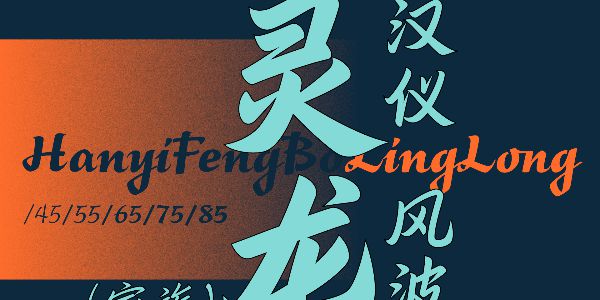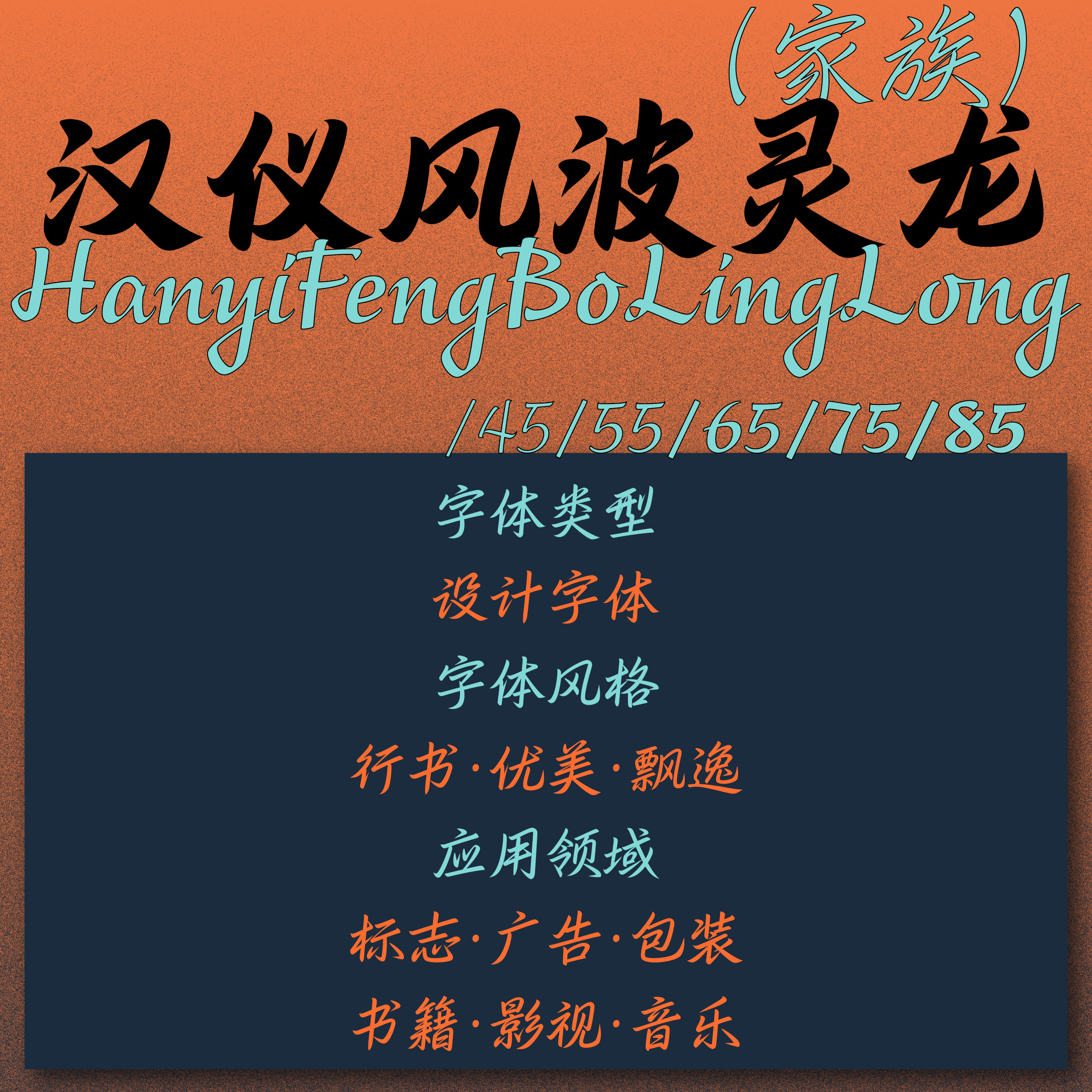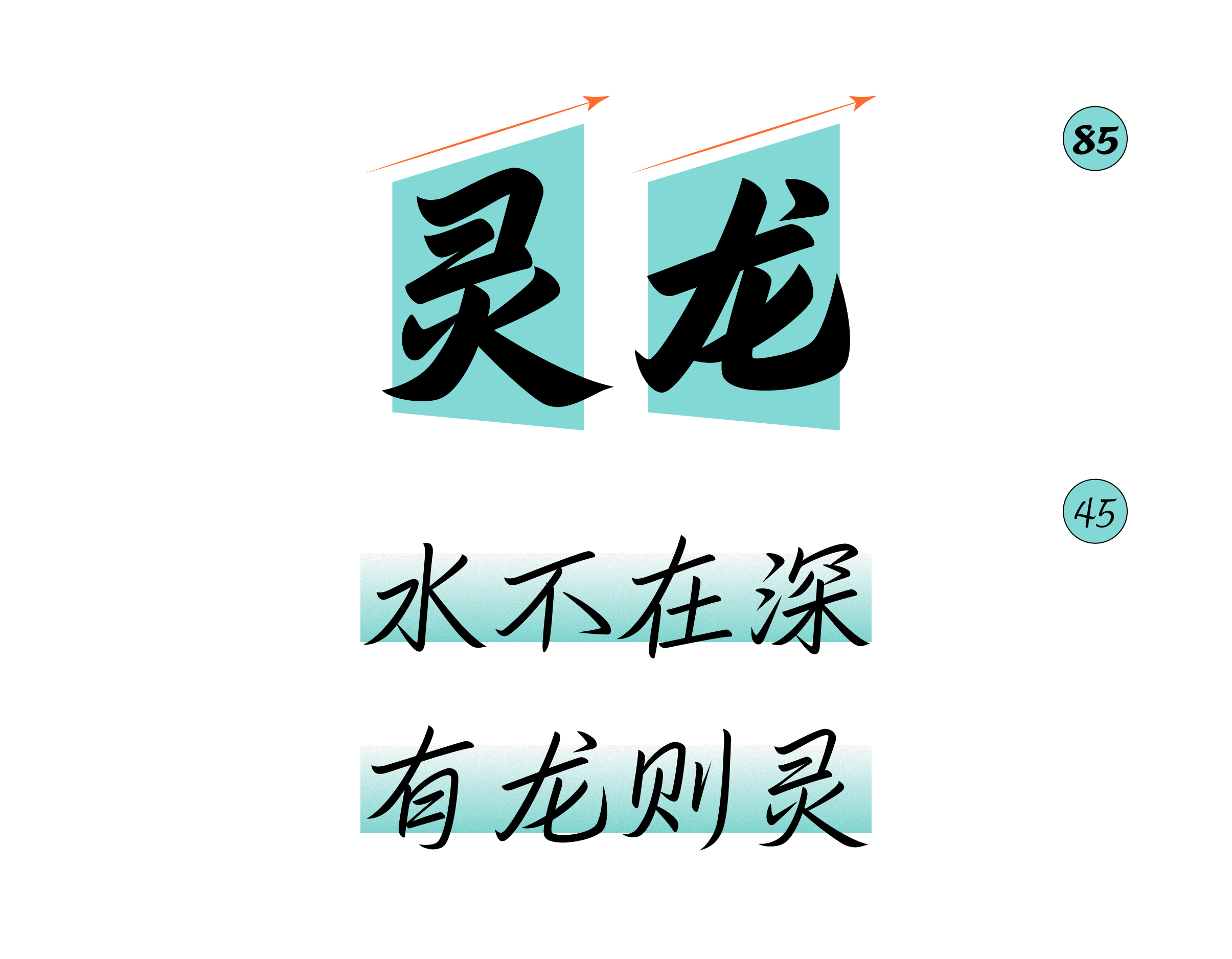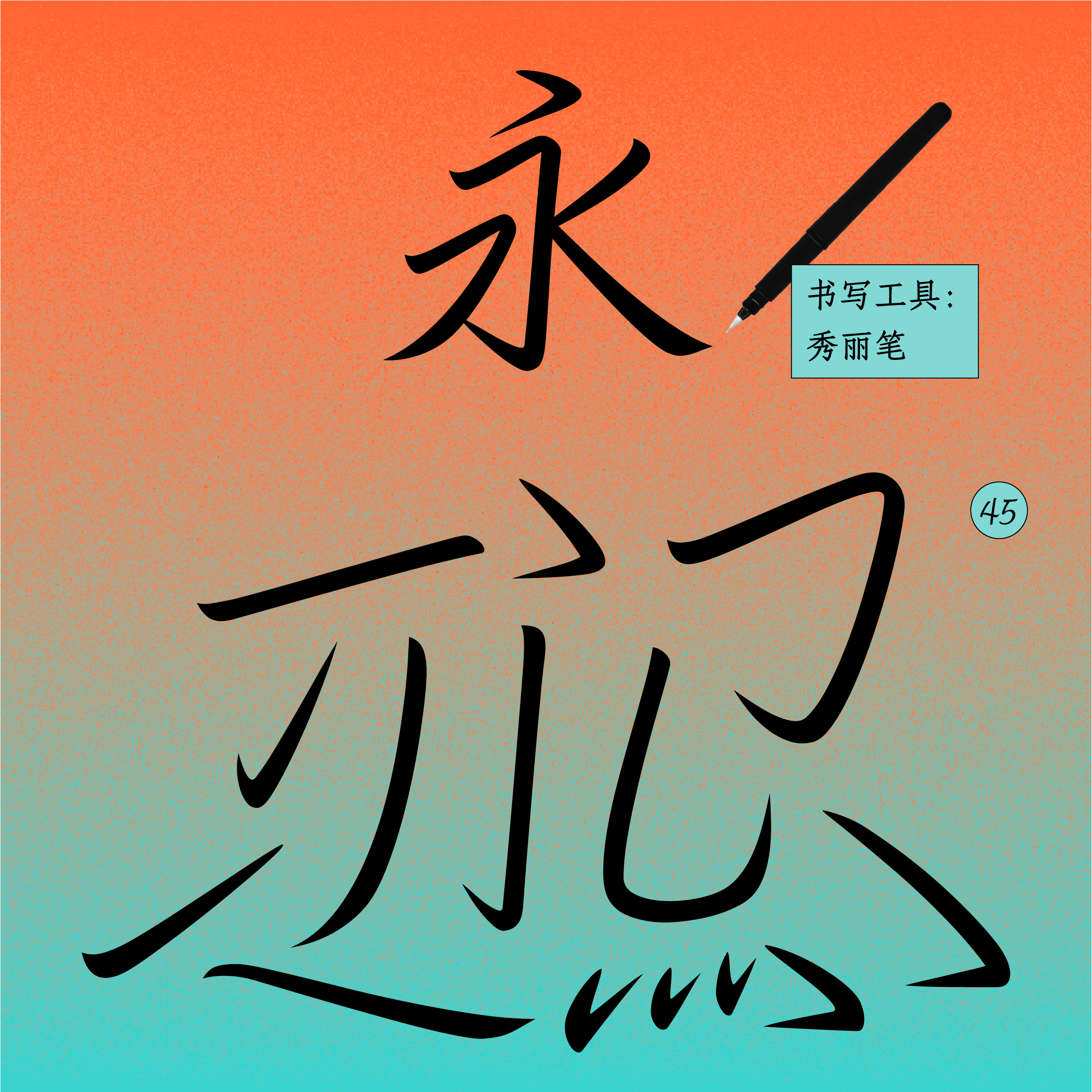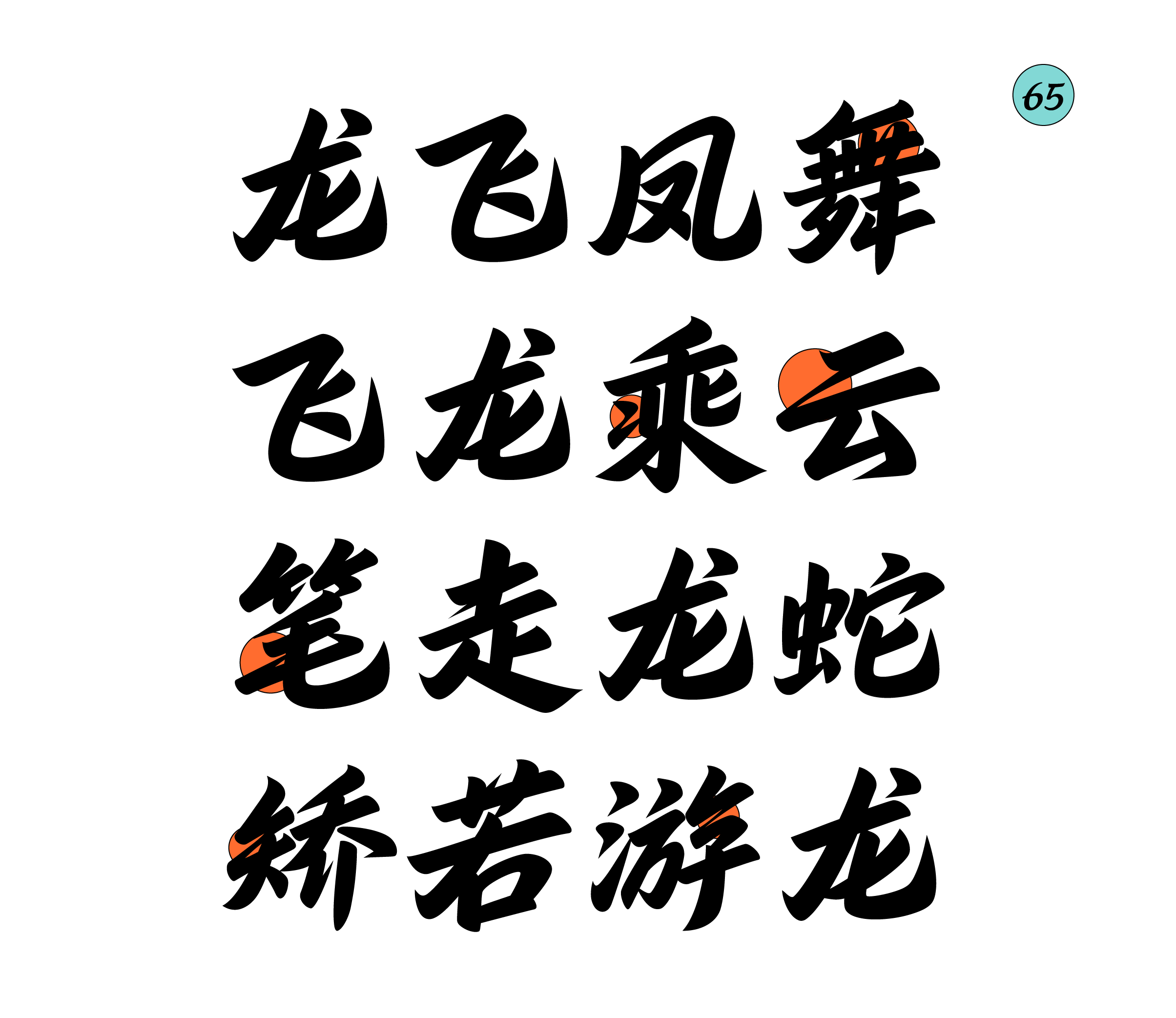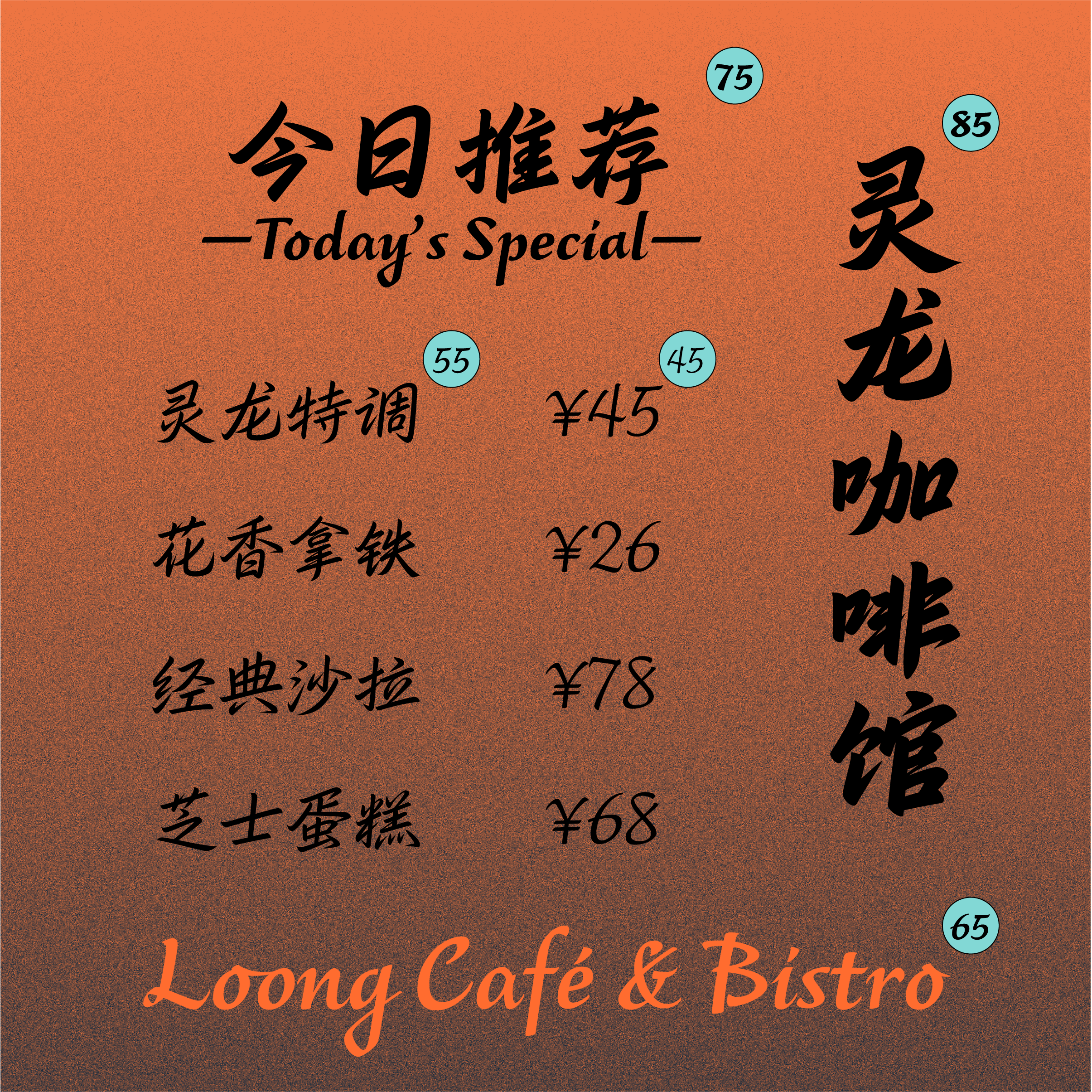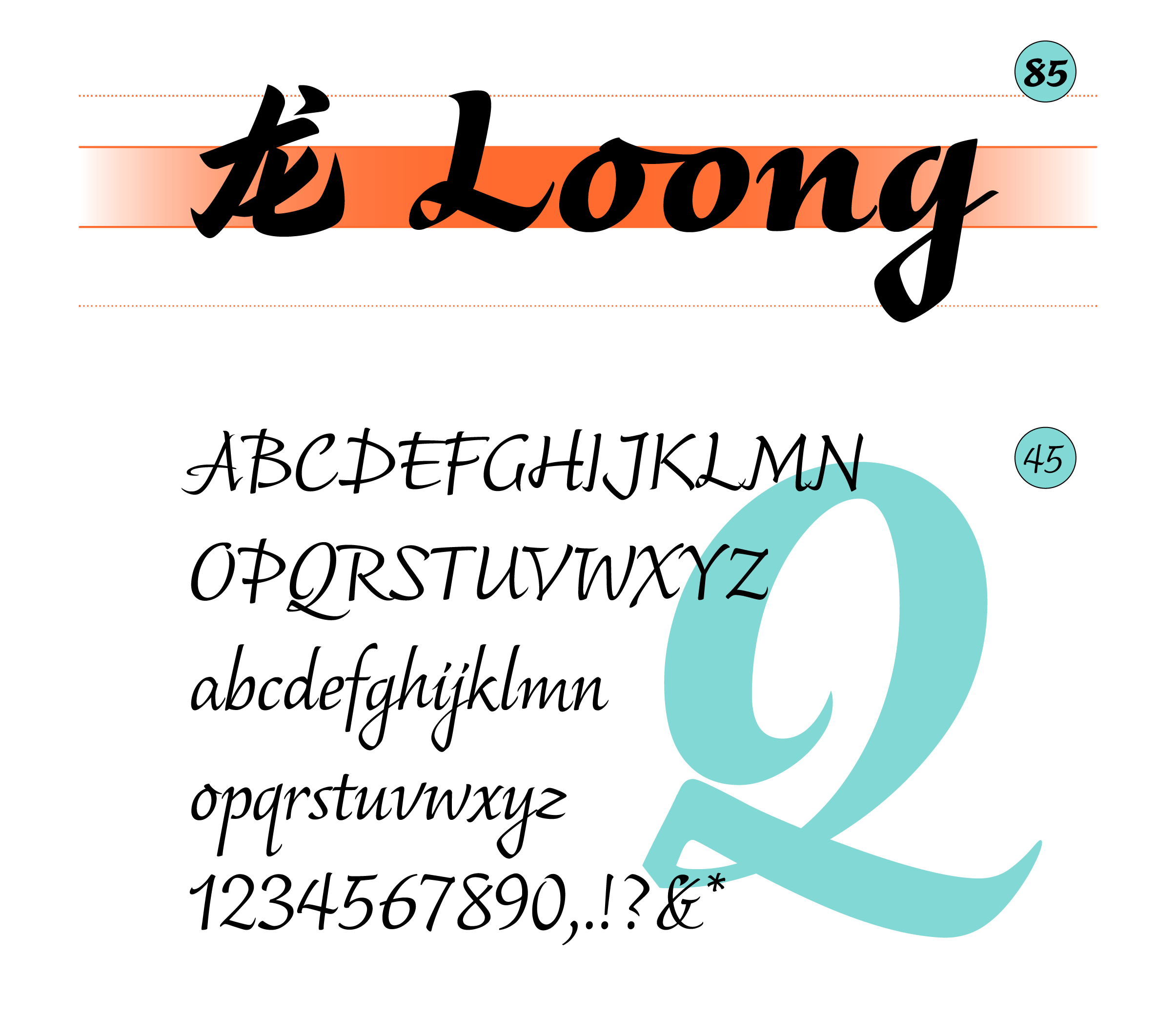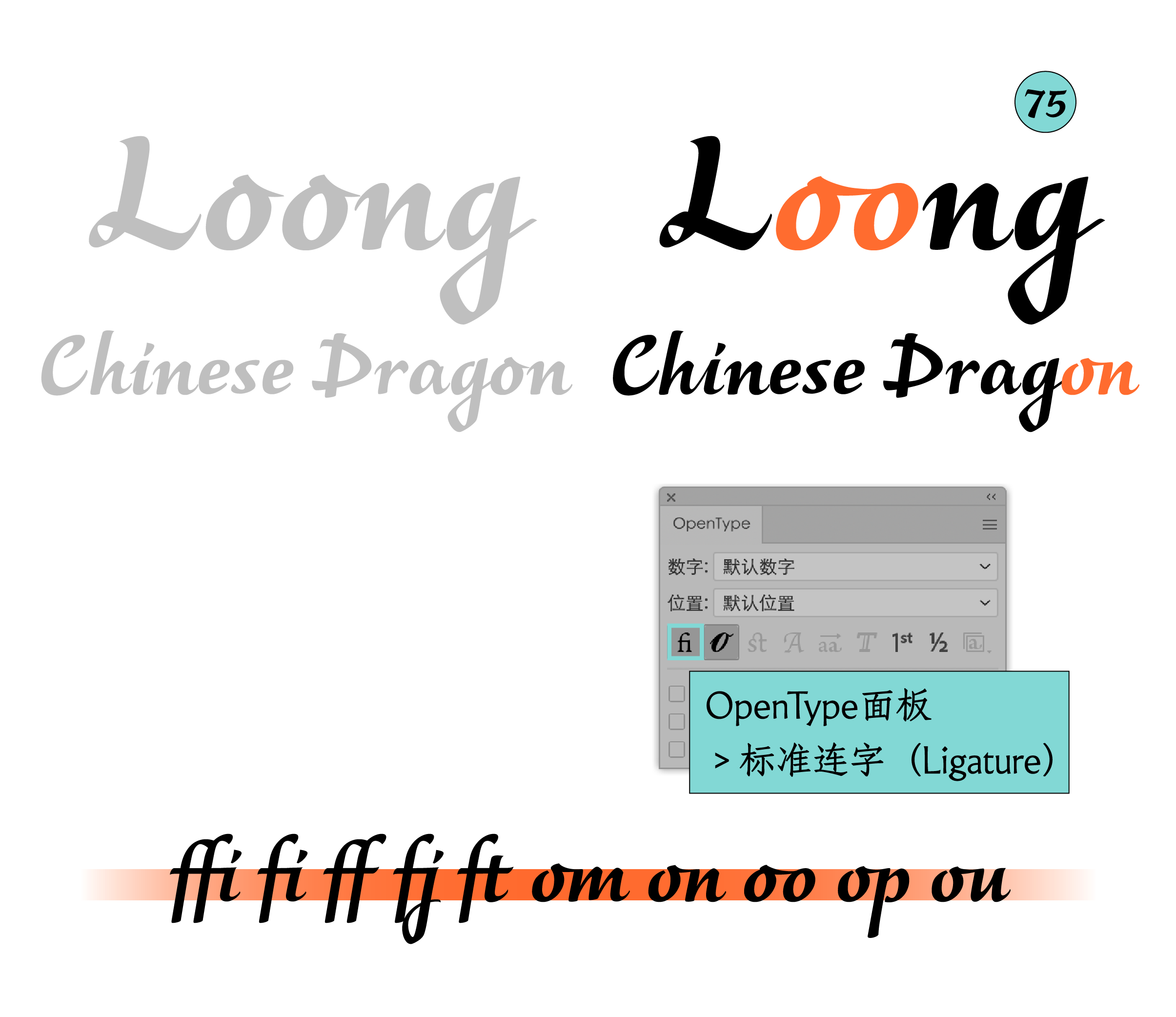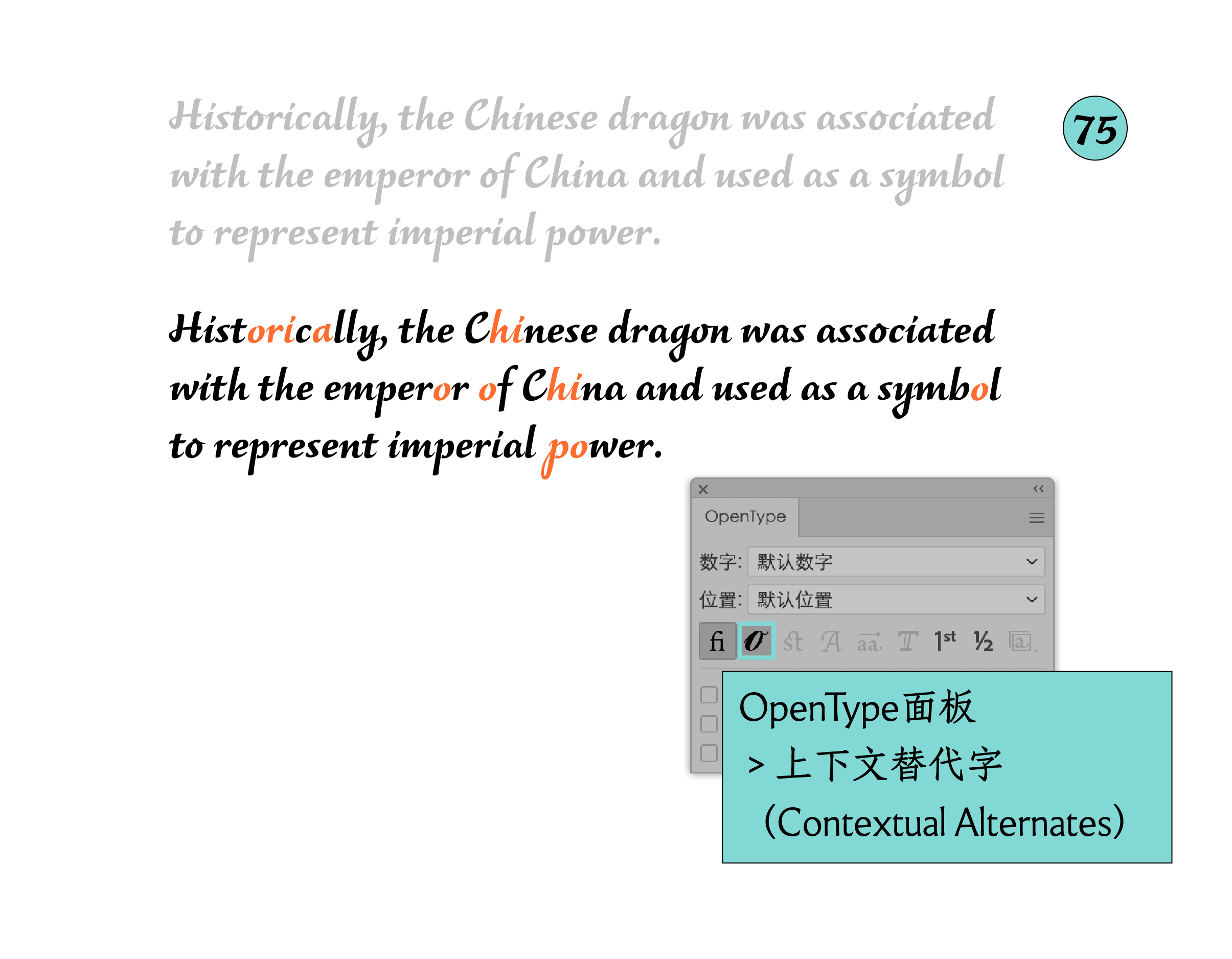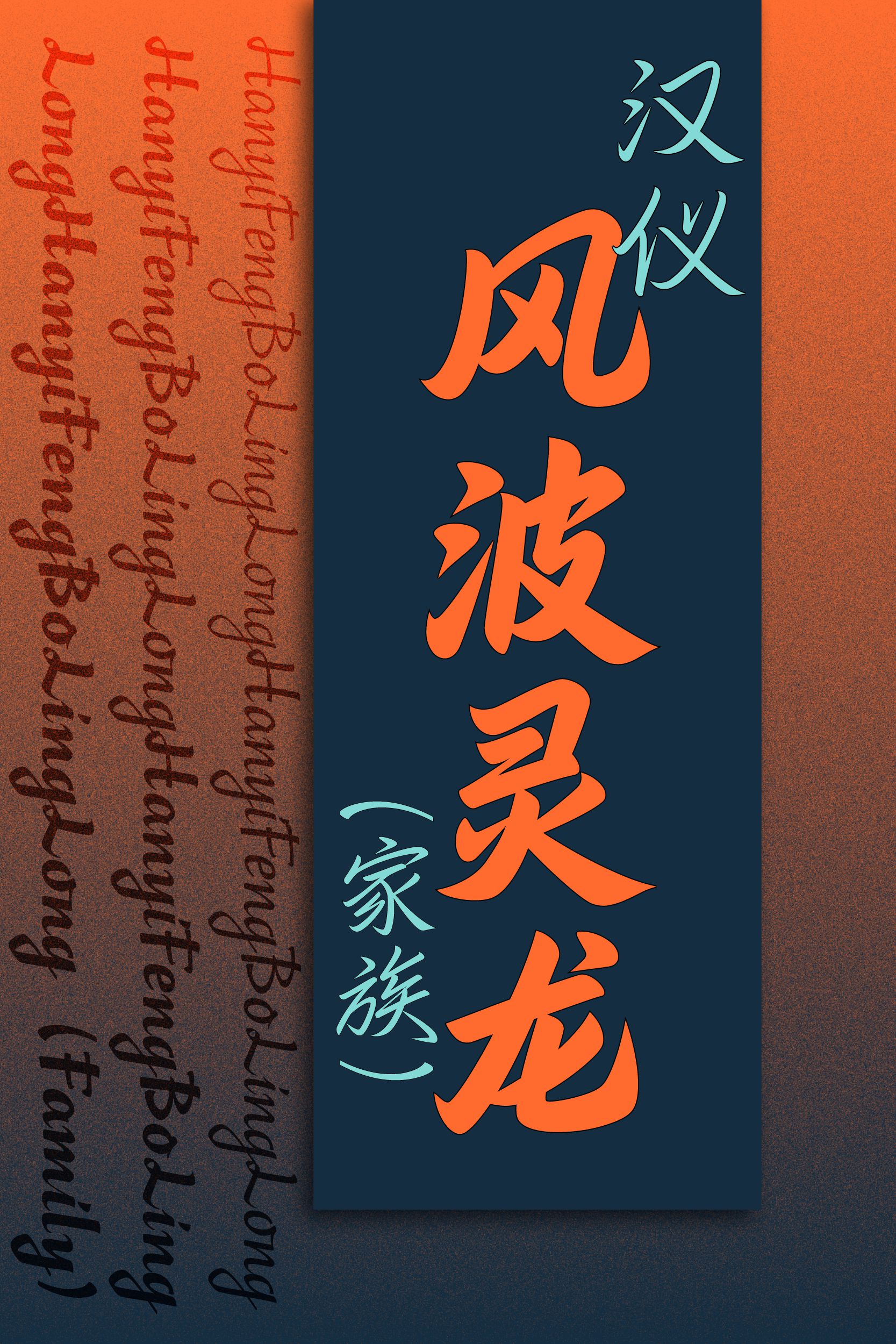
灵龙游动,跃然纸面
汉仪风波灵龙,是一款以西文软笔技法书写传统行书结构的设计字体,字形自然向右上方倾斜,线条优美飘逸,如灵龙游动,跃然纸面。这款字体的创作灵感源于作者使用秀丽笔书写英文花体字的经历,以秀丽笔书写重新诠释传统行书,西文设计以手写体(Script)风格与之匹配,中西合璧。
汉仪风波灵龙,共 5 款字重的家族化设计可以满足不同的排版需求:细款轻盈而迅捷,粗款灵动而优美,适用于广告、影视、综艺、音乐、书籍等多种使用场景。
字形结构左收右放,呈自然向右上方倾斜之势,似灵龙抬首。
笔画有着秀丽笔书写的特点:笔锋柔韧有弹性,线条流畅自然。
牵丝连带萦绕其中,体现出较快的书写速度。
细款轻盈而迅捷,笔画线条纤韧有力;粗款灵动而优美,笔画粗细对比较为强烈。
汉仪风波灵龙中文部分的书写灵感正是来源于西文书法,因此西文部分的设计以手写体(Script)风格与之匹配,书写速度较快,视觉效果灵动飘逸。
连字的设计使字形之间的连接更为流畅自然。
部分小写字母设计了多种替代字形,应用于文本中的不同位置,增添书写感。
汉仪风波灵龙适用于广告、影视、综艺、音乐、书籍等多种使用场景,或与基本款黑体、宋体搭配使用,凸显线条灵动、飘逸。